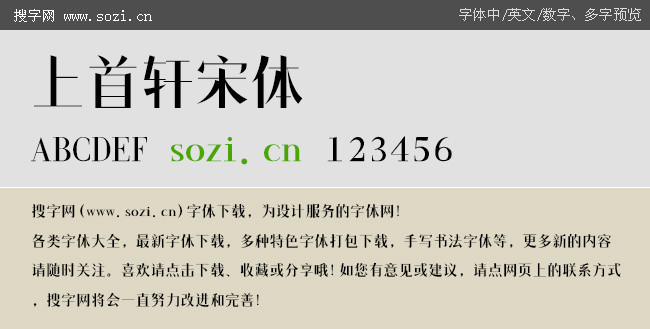
上首軒宋體
搜字網(wǎng)給大家提供一款上首軒宋體中文字體下載,這款字體字形簡潔時尚,筆畫粗細(xì)關(guān)系明確,使得字形空間結(jié)構(gòu)自然平衡;一改傳統(tǒng)宋體的間架結(jié)構(gòu),對其進(jìn)行大膽的創(chuàng)新設(shè)計(jì),讓其同時具有宋體的特點(diǎn),黑體的框架,符合現(xiàn)代審美識別要求。適用于海報設(shè)計(jì)、書籍裝幀、畫冊設(shè)計(jì)等廣告設(shè)計(jì)。